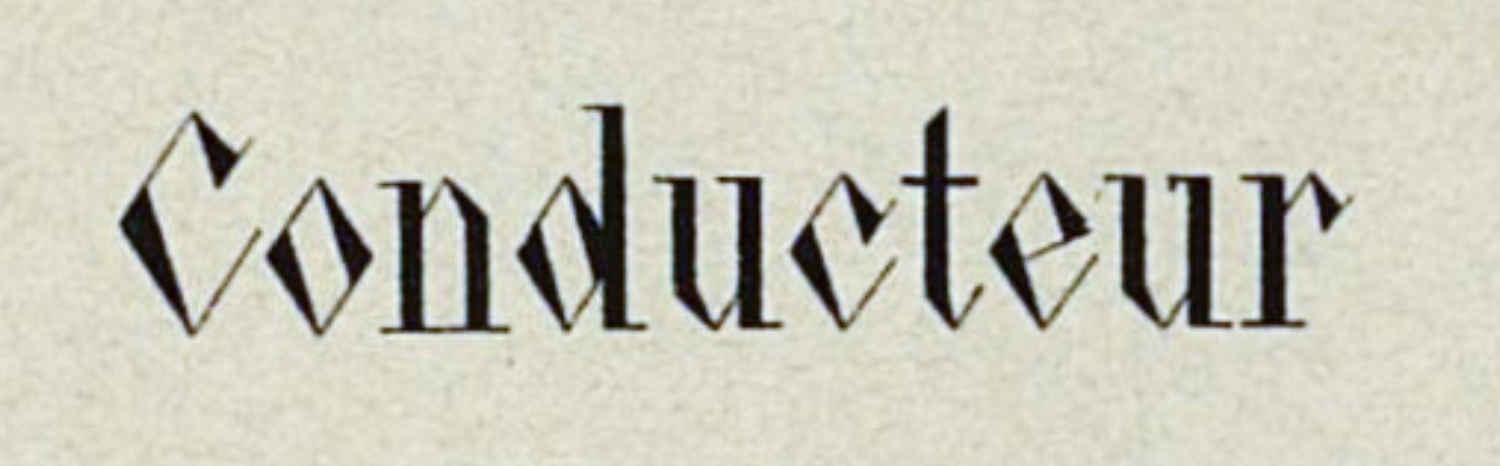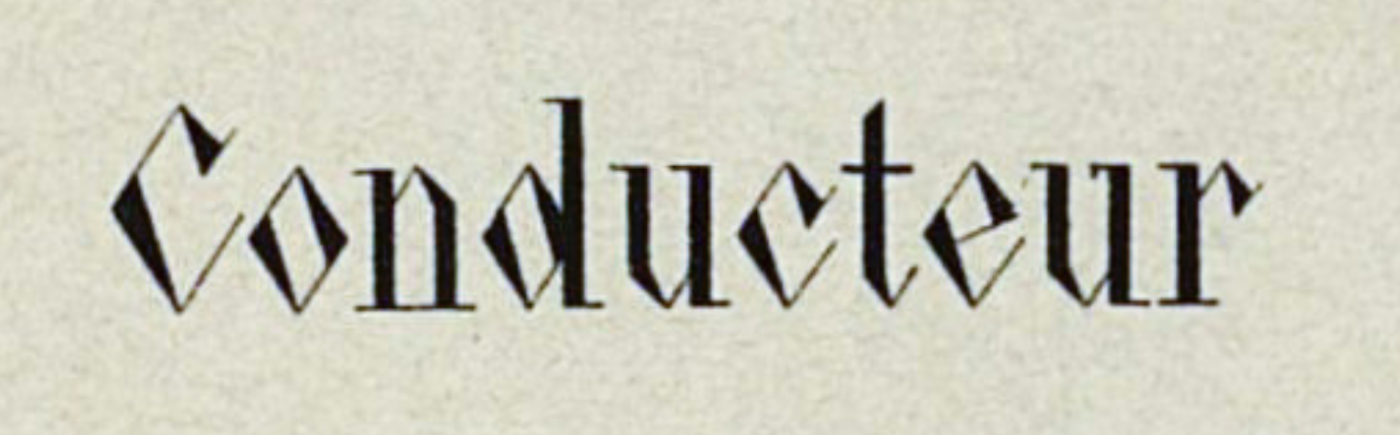
Suche zwei Schriftarten abgedruckt im "Schriften Atlas" vom Verlag Julius Hoffmann, Stuttgart, 1889
für Recherche Zwecke suche ich die unten angezeigten Schriften. Im von Ludwig Petzendorfer zusammengestellten Schriften Atlas werden diese auf Seite 280 namenlos unter der Kategorie "Amerikanische Zierschriften" gezeigt. An der 'Gutenberg' interessiert mich vorallem der skulpturale, dreidimensional Effekt sehr. (link: https://bibliotekus.artlebedev.ru/books/schriften-atlas/126/
Die Namen 'Gutenberg' und 'Conducteur' sind vermutlich nicht die Schriftnamen selbst.